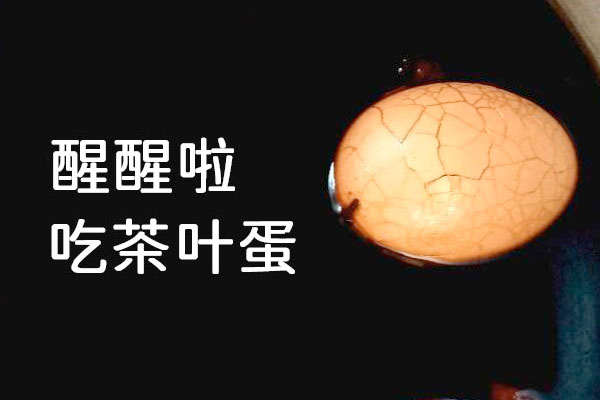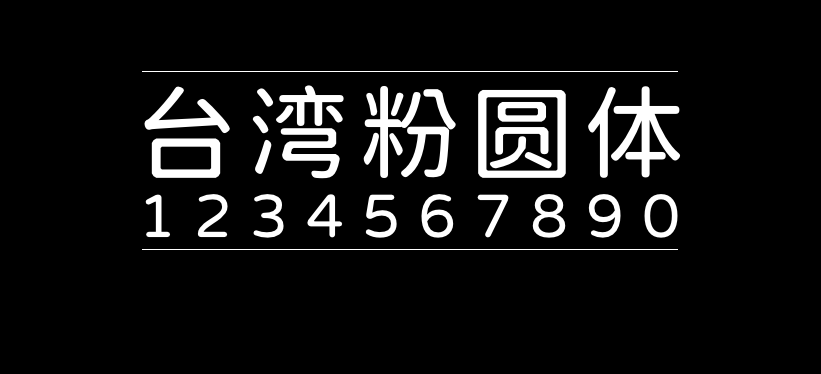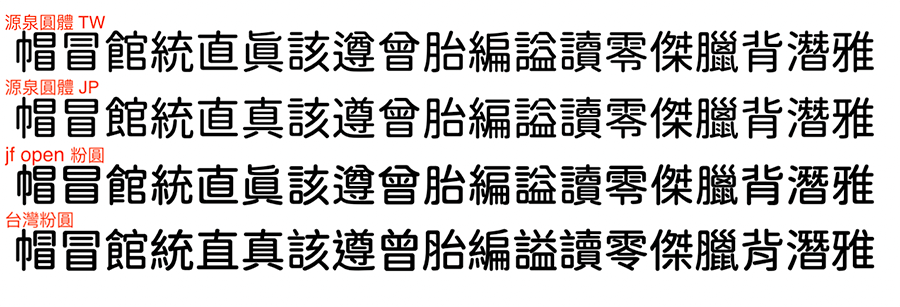
台湾粉圆
台湾粉圆(台灣粉圓)是台湾字体设计师Max基于思源黑体与jf open 粉圆修改创作的一个字体,大多的字是思源黑体为主,欧文还有部份的中文使用粉圆的中文字。
字体调整给人感受到最大区别是:思源黑体与jf open 粉圆的字腔大小不一样。粉圆较大,思源字腔较小,外放内收的结构在轮廓上看起来较有腰身,和传统汉字书法所讲究的美感相近,版面留白较多一点,较透气些。这个满神奇的,微调一下字的组成元件的位置或距离,文字传达出不一样的感觉,而且差异很显著。